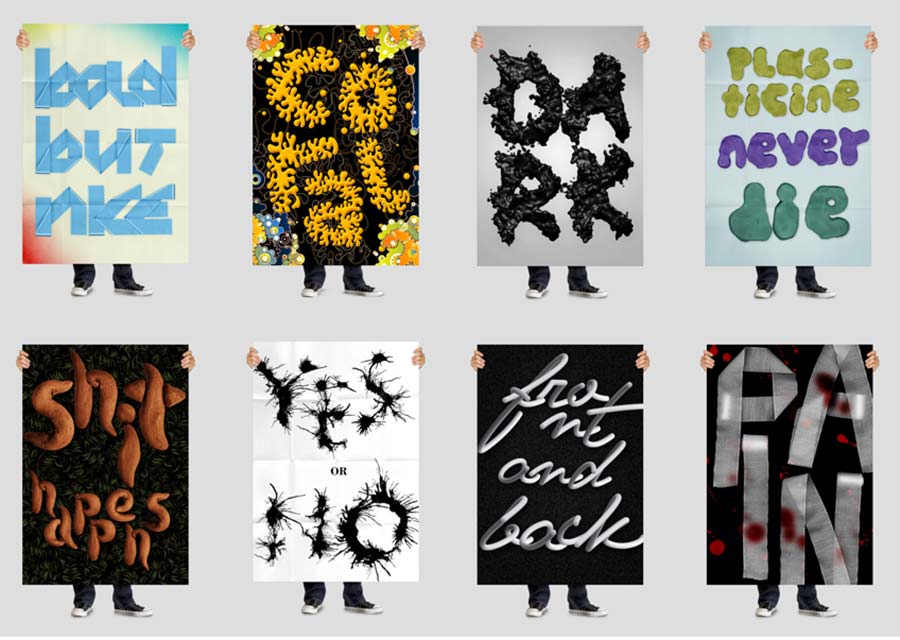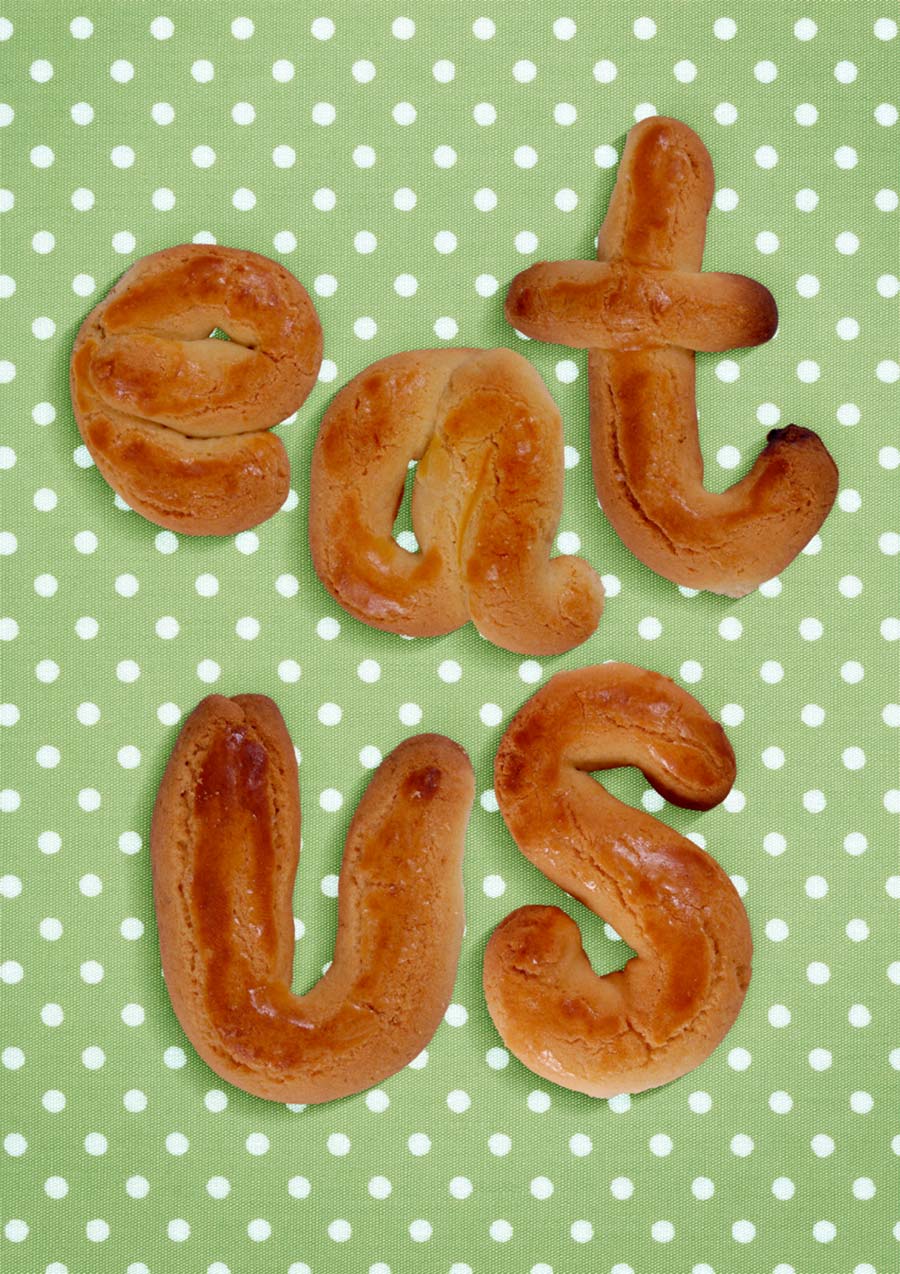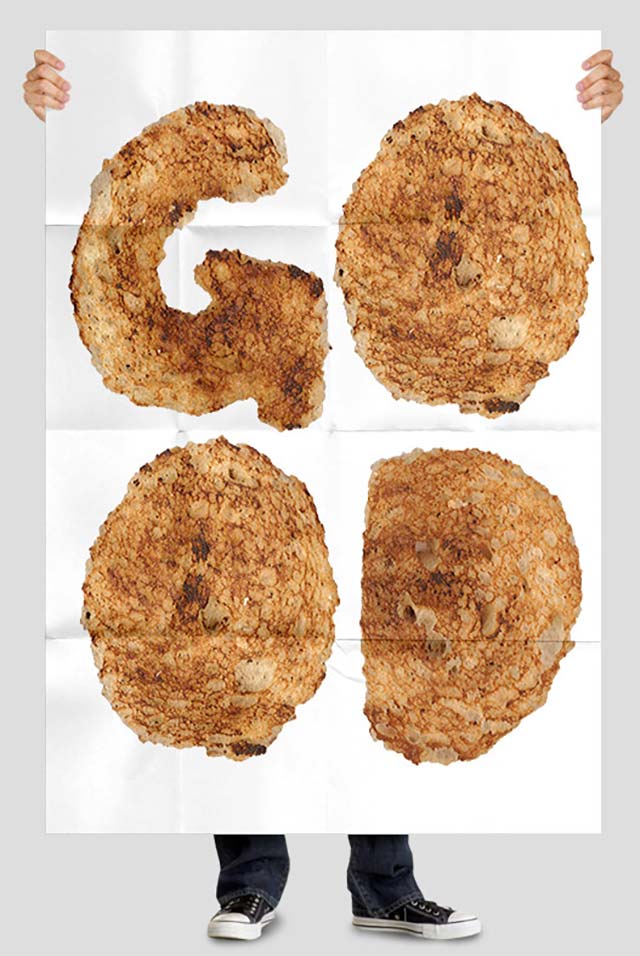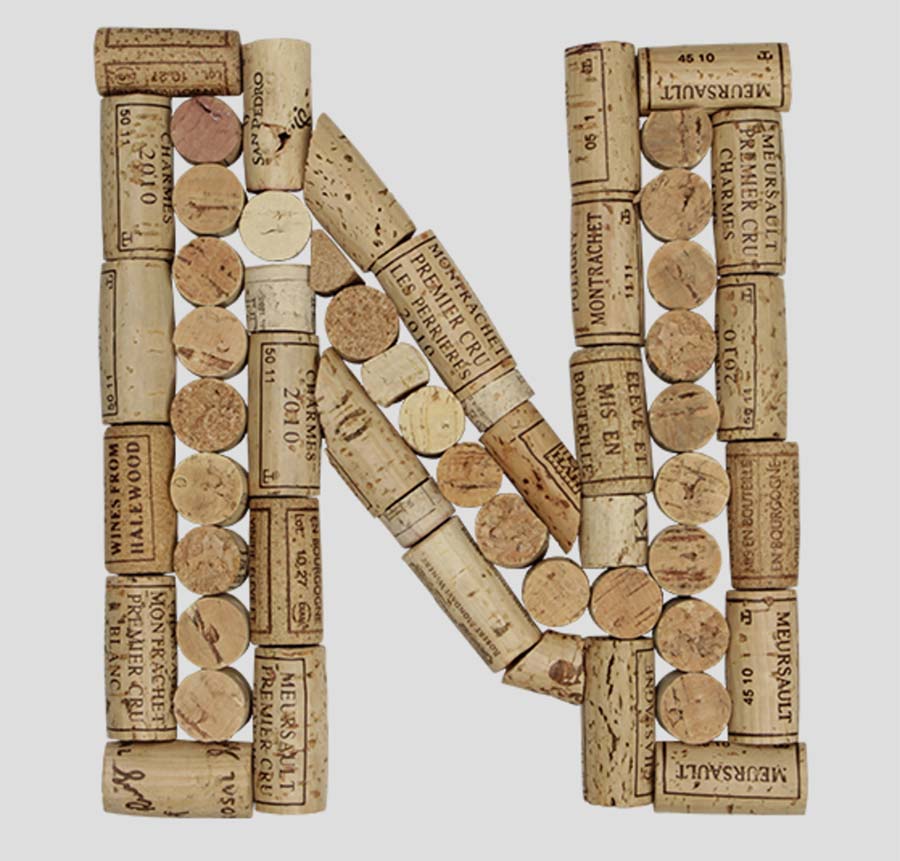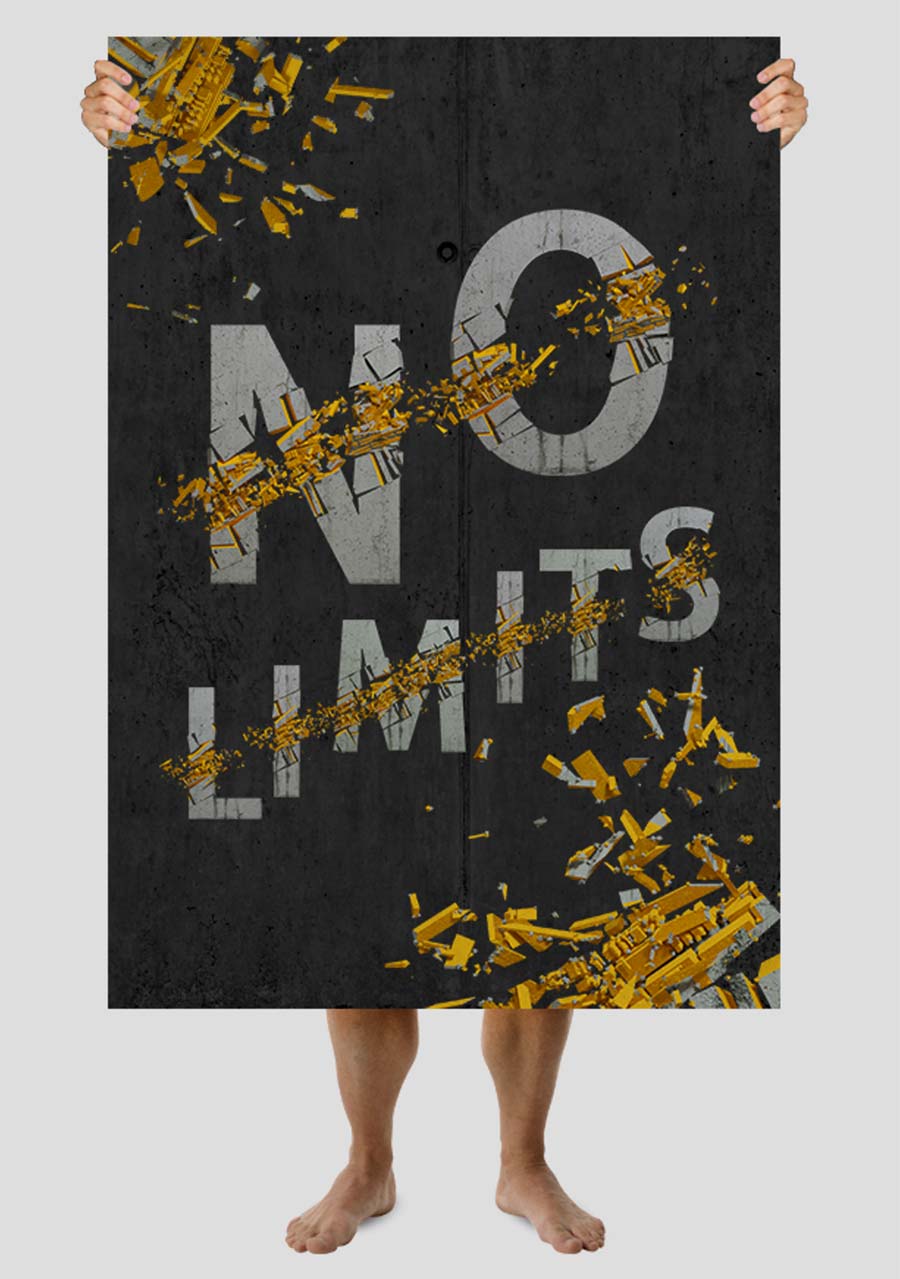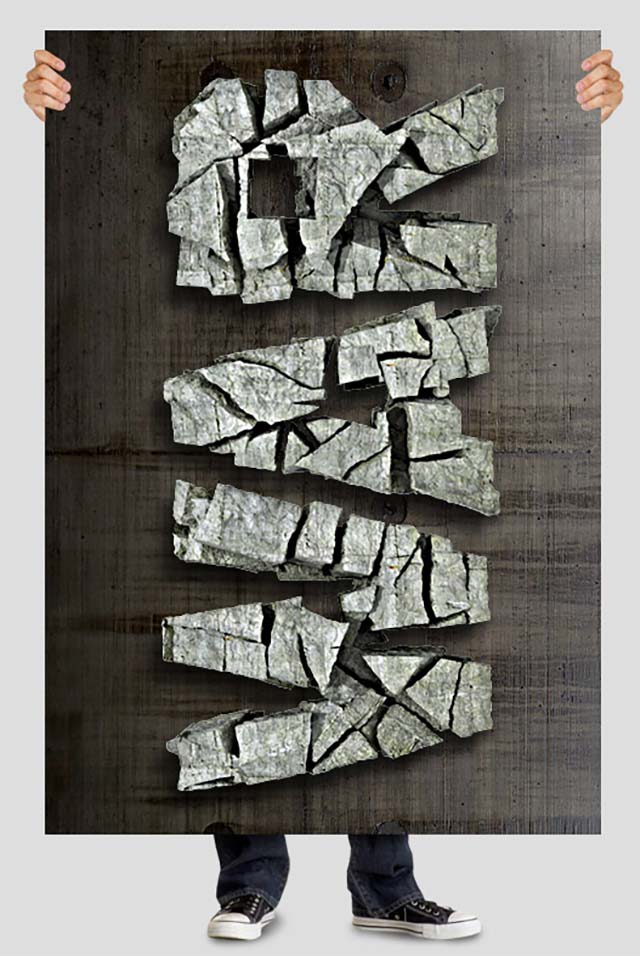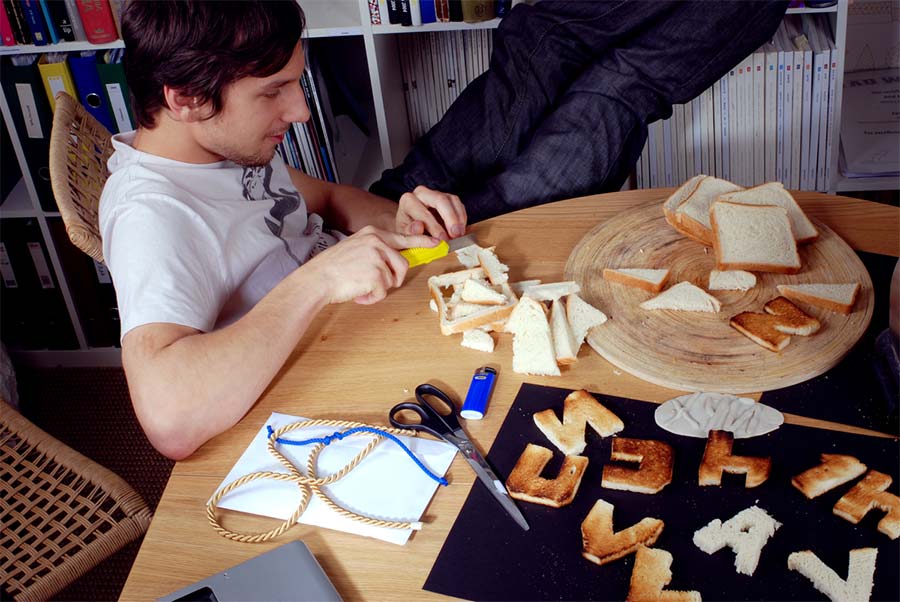
Kreatives aus Estland
Typografie-Spielereien: Handmadefont
2008 haben die Brüder Vladimir und Maksim Loginov die Schmieder origineller Schriftarten namens „Handmadefont“ gegründet. Sie lassen sich von allem inspirieren, was sie umgibt und erfreuen sich jeglicher Herausforderung, die Kunden und Freunde ihnen stellen. Eine Schrift aus Brot, Bacon oder Eiern? Kein Problem. Zwar scheinen nicht sämtliche verfügbare Schriftarten wirklich rein analog erstellt worden sein, aber da sind einige sehr skurrile bis originelle Varianten drunter.
„We make ideas real through beautifully crafted design.
We believe good ideas can be applied to anything.“
Weitere originelle Typografie-Spielereien gibt es auf der Website der beiden zu sehen. So zum Beispiel auch animierte bzw. bewegte Schriftarten: